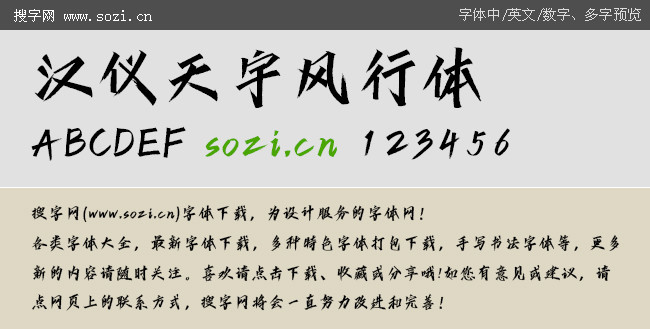
漢儀天宇風行體
搜字網(wǎng)給大家提供一款漢儀天宇風行體中文字體下載,漢儀天宇風行體將書法感和設計融為一體,創(chuàng)意特點鮮明,應用性明顯,節(jié)奏分明,充滿藝術(shù)張力,適合應用于藝術(shù)設計、平面宣傳設計、網(wǎng)頁設計等應用。(本字體為個人非商用版,如需要商用請聯(lián)系漢儀公司購買版權(quán))